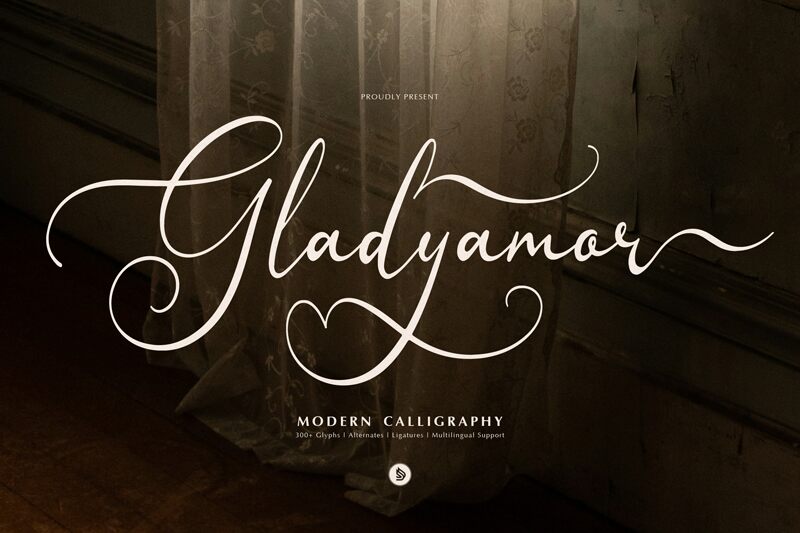
Gladyamor od Denustudios je moderní kaligrafické písmo zdarma s dlouhými, vzdušnými smyčkami a lehkým, módním rytmem. Písmena využívají elegantní a zúžené tahy, což písmu dodává vyvážený, romantický nádech, který působí spíše jako ručně psaný podpis než jako formální kaligrafie.
Skvěle se hodí pro svatební tiskoviny, beauty značky, butikové obaly, titulky časopisů i grafiku na sociální sítě, kde stačí jen pár slov k vyjádření stylu. Gladyamor jako bezplatné písmo výborně funguje u log, pozvánek a monogramů, protože jeho protáhlé křivky a otevřený pohyb dodávají krátkým jménům a iniciálám na výraznosti.